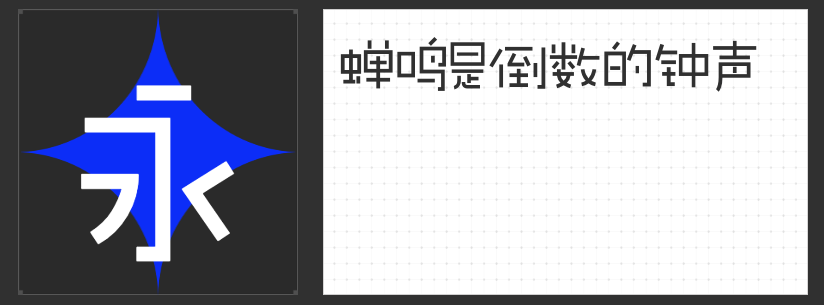
包装设计中的字体美学:四款风格化字体解锁创意新维度
在包装设计的视觉语言中,字体是传递品牌个性与产品温度的核心元素。一款独特的字体不仅能瞬间抓住消费者目光,更能通过形态与情感的共鸣,构建品牌与受众的深层联结。以下四款风格迥异的字体,以各自的设计哲学为包装设计注入鲜活生命力。
一、励字敲可爱简 常规
这款字体以手写圆润线条为基底,通过省略部分笔画与简化结构,创造出略带俏皮的视觉韵律。其直线的明快节奏与弧线的柔软触感交织,既保留了手绘的温度感,又以独特的“不完美”形态传递随性真诚的品牌态度。适用于食品、文创等需要营造亲切氛围的包装场景,让消费者在接触产品的瞬间感受到被温柔以待的用心。
二、字恋狂澄空 拂风
以“上松下紧”的动态结构打破传统字型的平衡感,通过重心偏移与字面变化赋予文字呼吸感。流畅的弧线与利落的直线碰撞出视觉张力,而平直切角与笔画断开的处理方式,则巧妙消解了锐度,让整体呈现出轻盈跃动的气质。这款字体尤其适合美妆、饮品等追求时尚感与年轻化的包装设计,通过字体的韵律感强化产品的灵动特质。
三、字恋狂漫野 絮风
直线构建的骨架中暗藏张弛有度的布白智慧,通过细微的大小错落与笔画断开处理,在理性秩序中注入野性生命力。去钩化的笔画设计让字体更显简洁利落,而灰度均匀的视觉效果则确保了远距离识别的清晰度。这款字体适用于户外用品、科技产品等需要平衡专业感与活力的包装场景,以克制的表达传递不羁的品牌精神。
四、字圈也字多肉体
将传统方折转化为流动圆环的“破方为圆”设计,让每个字符都成为独立的小剧场。封闭的圆形结构与Q弹的视觉质感,构建出充满游戏感的童话世界。这种字体尤其适合母婴产品、零食等需要唤醒消费者童心的包装设计,通过形态的趣味性消解商业感,让品牌与受众建立情感共鸣的桥梁。